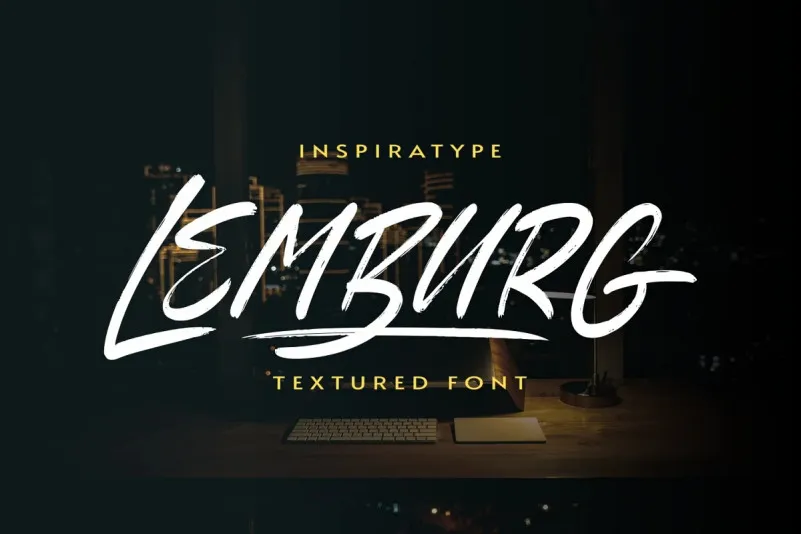
Lemburg Font
Lemburg Font é uma elegante fonte script criada para quem busca personalidade em seus projetos digitais. Com seu estilo marcado, letra a mão, traços e desgaste de gloop, esta fonte é perfeita para designers que valorizam um ar retrô e atual ao mesmo tempo. Seus componentes abrangentes incluem letras maiúsculas, minúsculas, números e pontuação, além de variâncias incríveis em cada caractere que oferecem alternativas do OpenType, ligaturas comuns e até mesmo swashes para uma maior personalização. Lemburg Font é perfeitamente adequado tanto para logotipos quanto para aplicativos de papel, como cartões de convite ou etiquetas. Suas variações únicas permitem que você personalize suas criações de acordo com sua necessidade, tornando-a uma escolha ideal para qualquer projeto de design digital.